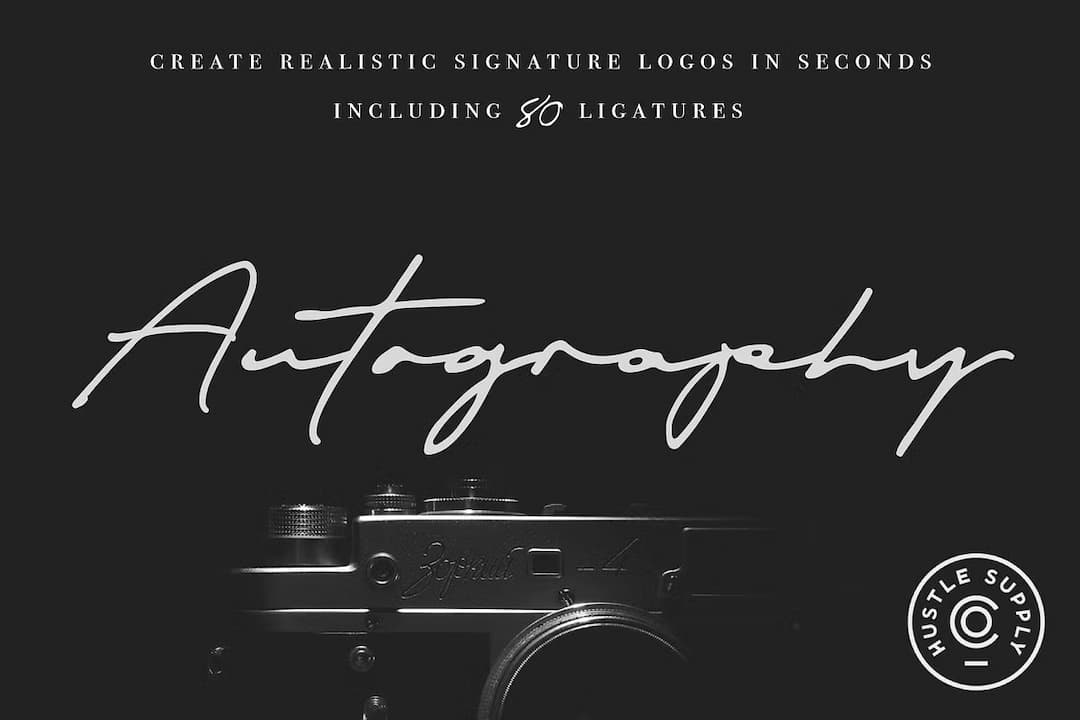
カッコいいリアルに近いシグネチャースクリプト。傾きが強く横の流れが強調されたタイプで、グリフは見ての通り潰れ気味で可読性はなかなか酷い(笑)。ただこれこそがいわゆる「署名」のリアルに近いだろう。大文字にはオルタネートはないが、小文字にリガチャーが80種ほどあって色々バリエーションが出せる。けど日本語のローマ字綴にはあまり当てはまるリガチャーがないのが常なので日本語名にはあまり期待はできない。珍しく6つのウェイトバリエーションがあるが、一番軽い Regular と一番重い Super Bold でもほとんど違いは見いだせないほど微妙である。